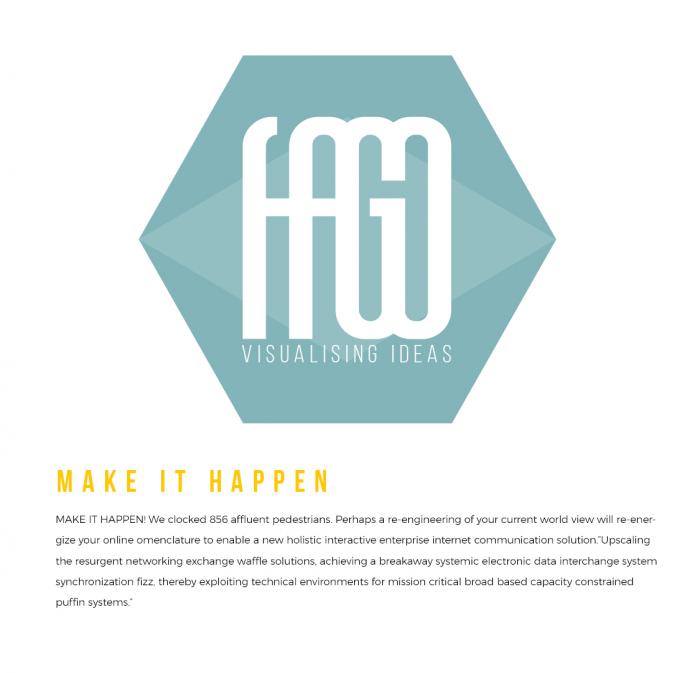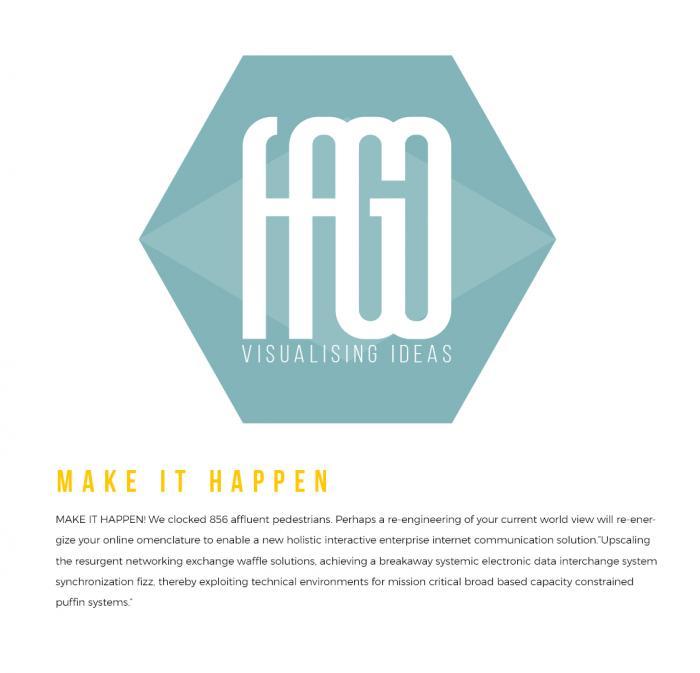
Suche Brotschrift, die zur Bebas Neue passt
ich fummel gerade an einem Corporate Design herum, das Logo ist fast fertig! Nun bin ich am überlegen, was man sich für Hausschriften zulegt.
Weil im Logo die Bebas Neue verwendet wurde, würde ich die auch beibehalten, aber da wäre noch die Frage nach einer schicken Brotschrift.
Das Logo habe ich angehängt sowie eine Idee für den Fließtext - das ist die Montserrat. Gefällt mir soweit schon ganz gut, aber vielleicht habt ihr noch bessere Ideen?
Schrift sollte natürlich gut lesbar sein, dennoch geht es hier um ein Kreativbüro, und da ist natürlich die Optik ausschlaggebend. Schick, aber nicht langweilig schwebt mir da so vor :-)